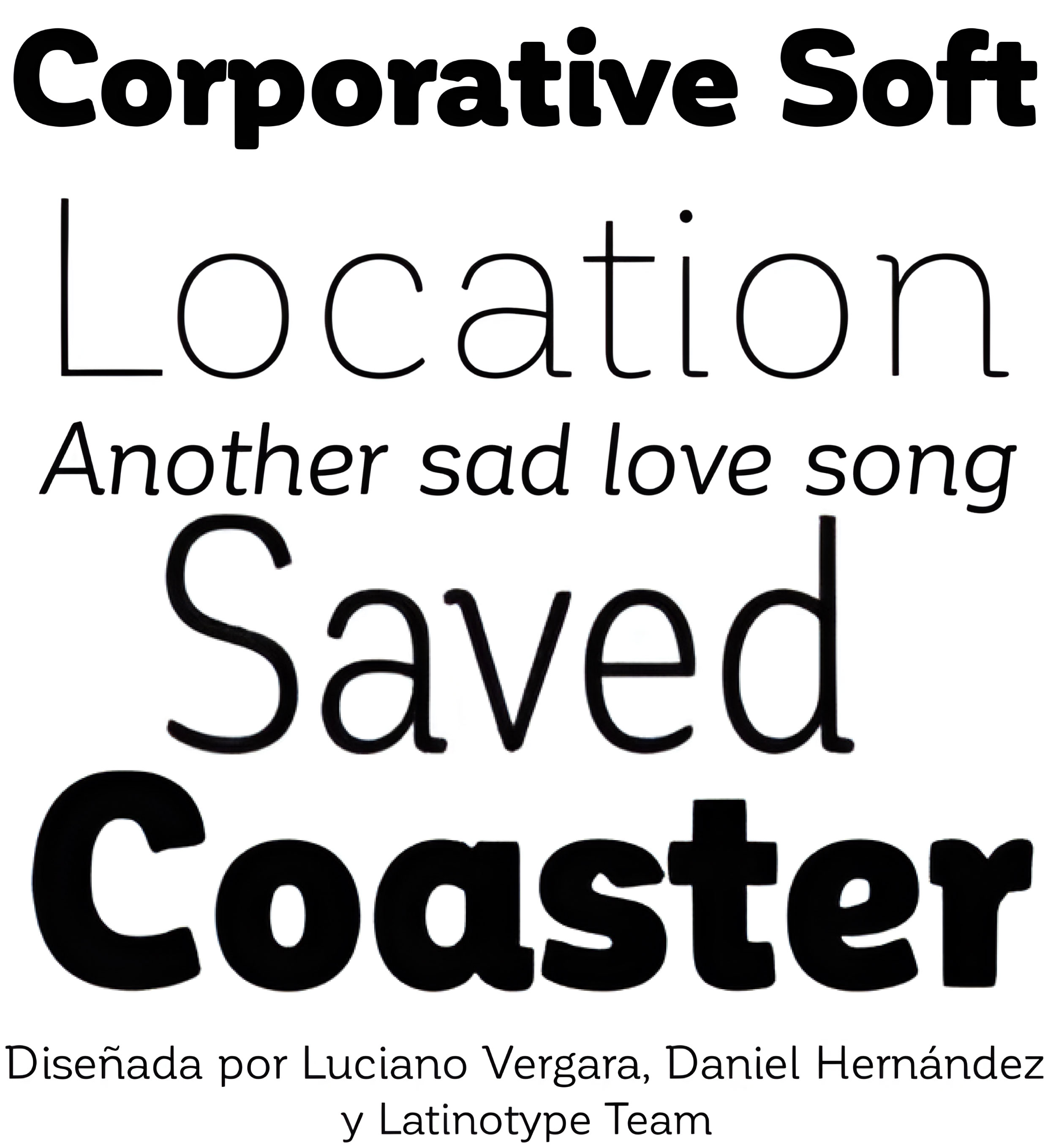
| Año | 2015 |
| Créditos | Luciano Vergara, Daniel Hernández |
| Descripción | Corporative Soft es la versión ligeramente redondeada de Corporativo. Esta fuente tiene una marcada personalidad y rasgos distintivos, lo que la hace adecuada para ser utilizada en textos de gran tamaño. Al mismo tiempo, la suave transición de líneas rectas a curvas confiere a la fuente una sensación más amable. Este tipo de letra es la elección perfecta para logotipos, carteles, señales, marcas, envases, etc. Corporative Soft incluye el conjunto estándar de 350 caracteres de Latinotype, lo que permite utilizar la fuente en 128 idiomas diferentes. Corporative Soft ofrece a los usuarios una amplia gama de caracteres, pesos y anchuras para cada proyecto. Combinando distintas variantes, los diseñadores pueden conseguir los mejores resultados. La familia consta de 64 fuentes: una familia básica que incluye 8 pesos más cursiva, una familia alternativa de 8 pesos con cursiva a juego y 2 familias condensadas, una normal y otra alternativa, ambas con cursiva. Corporative Soft fue creada por LatinotypeTeam y desarrollada por Javier Quintana, Eli Hernández y Rodrigo Fuenzalida, bajo la supervisión de Luciano Vergara y Daniel Hernández. |
| Familia(s) | Corporative Soft |
| Estudio | Latinotype |